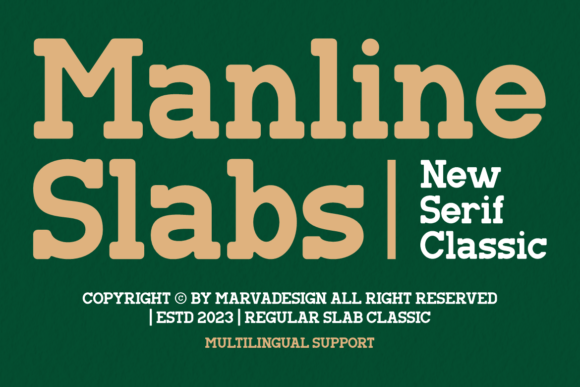
Manline Slabs - Fonte Slab Serif para Títulos e Design de Logotipos
Manline Slabs é uma fonte slab serif que combina a força e a solidez do design slab serif com formas de letras limpas e bem equilibradas. Seus serifs espessos e em bloco e traços uniformes conferem ao seu texto uma sensação estável, imponente e, ao mesmo tempo, atemporal — ideal para projetos que exigem legibilidade e impacto, como embalagens, logotipos, sinalização ou layouts editoriais.
Como uma fonte slab serif — uma categoria conhecida por seus estilos serifados ousados e confiáveis — a Manline Slabs oferece um apelo tanto vintage quanto contemporâneo. Seu caráter versátil a torna adequada para títulos de destaque ou textos de marca, bem como para designs impressos e digitais onde clareza e estilo devem andar juntos.
- Design tipográfico slab-serif com serifas arrojadas em formato de bloco e traços uniformes.
- Estilo slab-serif arrojado — excelente para transmitir confiabilidade, força e um apelo clássico.
- Letras nítidas e legíveis mesmo em tamanhos médios — ideal para títulos e textos de tamanho moderado.
- Estética clássica de fontes slab serif que combina bem com diversos estilos de design (moderno, vintage, rústico, minimalista).
P: A fonte Manline Slabs é adequada para parágrafos longos ou para o corpo do texto?
A: É mais indicado para títulos, cabeçalhos, textos de embalagens, logotipos, sinalização ou outros textos com foco no design, em vez de textos longos — as fontes slab serif têm serifas em negrito e são mais adequadas para títulos ou textos de tamanho médio. Fontes slab serif como essa geralmente têm melhor desempenho quando usadas para designs impactantes. -